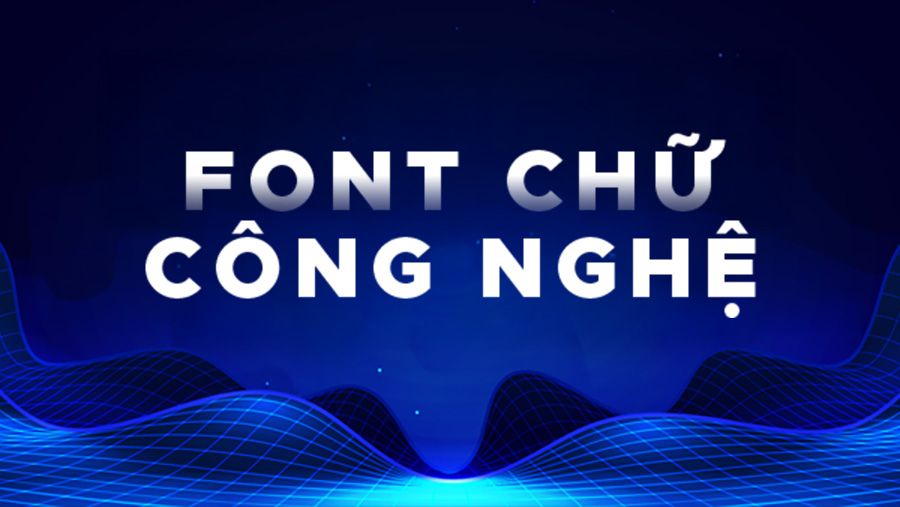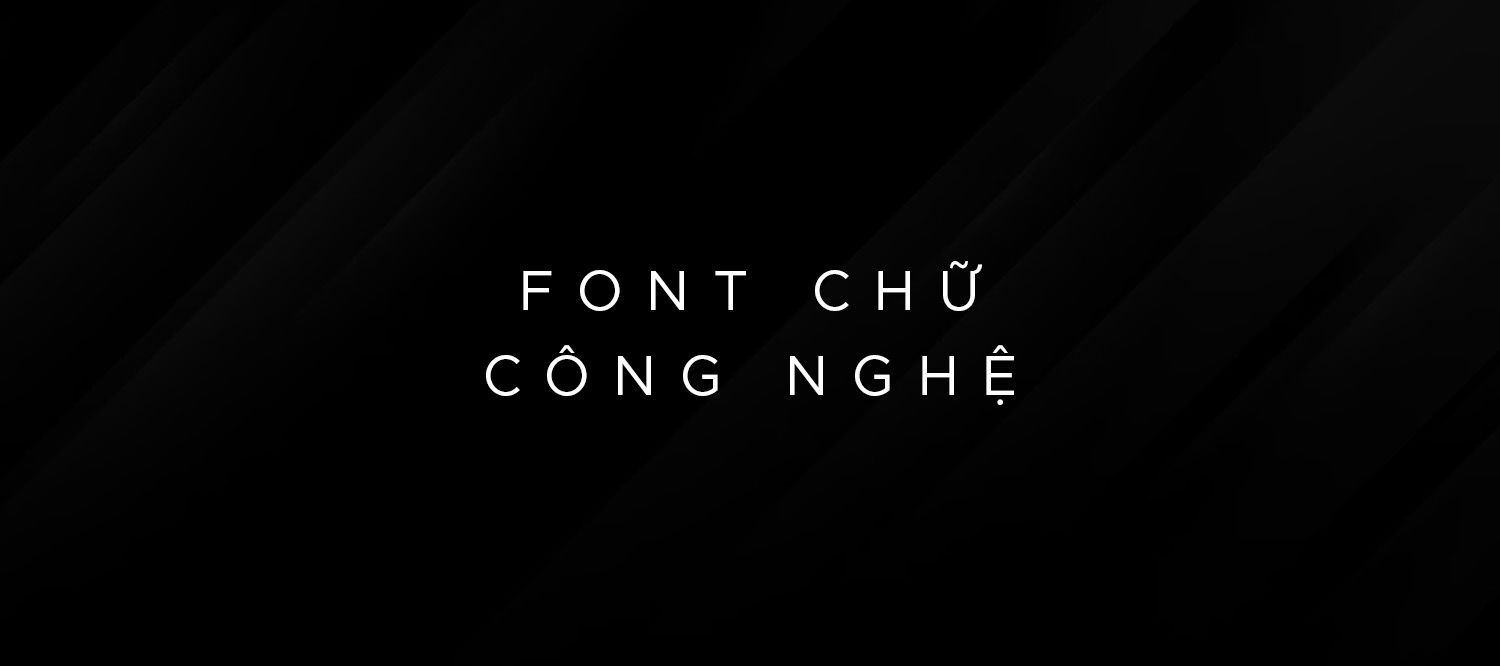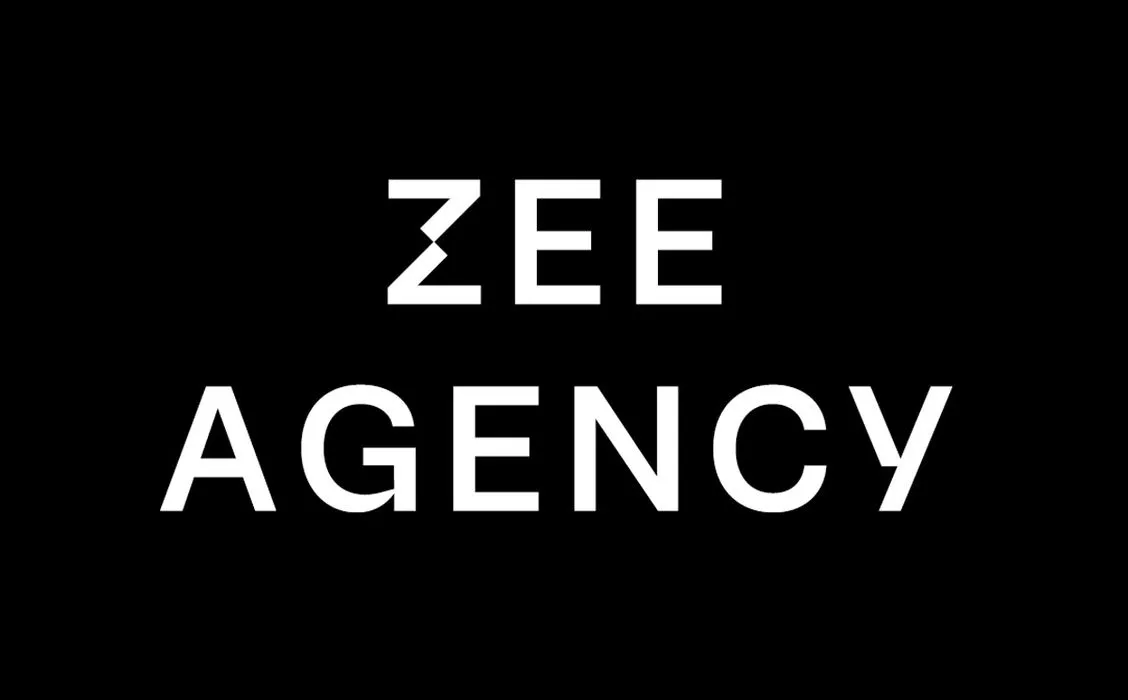
[Tải Xuống] 15+ Font Chữ Công Nghệ Việt Hóa Miễn Phí & Có Phí Mới Nhất 2025
Giới thiệu chung
Năm 2025, font chữ công nghệ nổi lên như một xu hướng quan trọng trong ngành thiết kế đồ họa. Không chỉ mang đến sự hiện đại, mạnh mẽ và đầy tính tương lai, những font này còn giúp designer truyền tải thông điệp sáng tạo trong nhiều lĩnh vực: từ UI/UX, branding, esports cho đến poster sự kiện công nghệ.
Điểm đặc biệt, nhiều bộ font đã được Việt hóa đầy đủ dấu tiếng Việt, nhờ đó trở nên thân thiện và dễ ứng dụng hơn cho cộng đồng thiết kế trong nước. Trong bài viết này, chúng ta sẽ cùng khám phá 15+ font chữ công nghệ miễn phí & có phí mới nhất 2025, kèm link tải trực tiếp từ S99.vn.
Font chữ công nghệ là gì?
Font chữ công nghệ (Technology Fonts) là khái niệm chỉ những kiểu chữ được thiết kế với đường nét góc cạnh, dứt khoát, mang hơi thở hiện đại và tương lai. Đặc trưng của chúng là tạo cảm giác mạnh mẽ, tinh gọn và giàu tính ứng dụng trong các sản phẩm số.
Các font này thường có cấu trúc chữ vuông vức, chắc chắn và đôi khi kết hợp hiệu ứng sáng, cắt chéo hoặc phong cách sans-serif tối giản. Nhờ sự đa dạng này, font chữ công nghệ trở thành lựa chọn hoàn hảo cho logo công nghệ, thương hiệu hiện đại, thiết kế UI/UX và poster mang hơi hướng sci-fi, futuristic.
Danh sách 15 font chữ công nghệ Việt hóa
1. Font chữ DFVN Pexel Grotesk Việt hóa – Hiện đại, tối giản và miễn phí
DFVN Pexel Grotesk đưa người xem quay lại nét đẹp của máy đánh chữ cổ điển nhưng đã được thổi vào hơi thở mới. Những đường chữ vuông vắn, gọn gàng tạo sự chắc chắn và tinh tế, vừa đủ để làm tiêu đề nổi bật nhưng cũng không kém phần thanh thoát cho UI hiện đại.
2. Font chữ VL Monologue Việt hóa – Cứng cáp, hiện đại cho thiết kế công nghệ
Điểm mạnh của SVN Cintra nằm ở sự đa năng. Với chữ dày, rõ nét, font này được ưa chuộng trong esports, game, xây dựng và cả cơ khí. Tính ứng dụng rộng cùng cảm giác hiện đại giúp nó luôn nằm trong top lựa chọn cho các dự án thiết kế chuyên nghiệp.
3. Font chữ công nghệ SVN Cintra Việt hóa – Mạnh mẽ và đa năng trong ứng dụng
Điểm mạnh của SVN Cintra nằm ở sự đa năng. Với chữ dày, rõ nét, font này được ưa chuộng trong esports, game, xây dựng và cả cơ khí. Tính ứng dụng rộng cùng cảm giác hiện đại giúp nó luôn nằm trong top lựa chọn cho các dự án thiết kế chuyên nghiệp.
4. Font chữ UTM Neutra Việt hóa miễn phí – Tối giản nhưng cực kỳ mạnh mẽ
UTM Neutra toát lên sự cân bằng giữa tối giản và sức mạnh. Những nét chữ vuông vức, sắc sảo tạo cảm giác vững chắc, rất hợp với thiết kế kiến trúc, branding công nghệ và poster quảng cáo cần sự sang trọng, hiện đại.
5. Font chữ SVN Kelso Việt hóa – Neon độc đáo, hiện đại và ấn tượng
SVN Kelso làm người ta liên tưởng đến những bảng đèn neon rực rỡ nơi phố thị về đêm. Hiệu ứng phát sáng độc đáo của font này cực kỳ phù hợp với game, nhạc hội hay những poster cần sự bắt mắt, sôi động.
6. Font chữ công nghệ SVN Mission X Việt hóa – Mạnh mẽ, đậm chất gaming
SVN Mission X mang đậm hơi thở của thế giới game và esports. Những đường chữ góc cạnh, dứt khoát truyền tải sức mạnh và tốc độ, khiến nó trở thành lựa chọn lý tưởng cho banner giải đấu, logo gaming hoặc thương hiệu công nghệ.
Việt hóa: SVN Team
7. Font chữ Zee Display Việt hóa – Không chân, tối giản và hiện đại
Zee Display mang đến sự rõ ràng và trực quan. Các đường chữ không chân dày, chắc giúp font giữ vững khả năng hiển thị sắc nét trên mọi thiết bị, từ giao diện ứng dụng đến poster quảng cáo công nghệ.
Tác giả gốc: Nach Oh!
Việt hóa: Team Zee
8. Font chữ TH Radley Sans Việt hóa – Thể thao khỏe khoắn và mạnh mẽ
TH Radley Sans toát lên tinh thần thể thao với từng đường chữ khỏe khoắn. Sự mạnh mẽ trong thiết kế khiến font trở thành công cụ đắc lực cho banner esports, logo phòng gym hay các dự án branding năng động.
Tác giả gốc: Mukhlis Muhammad
Việt hóa: TH Team
9. Font chữ TH Bernat Việt hóa – Serif thanh lịch kết hợp hiện đại
TH Bernat là sự hòa quyện giữa cổ điển và hiện đại. Với đặc trưng serif tinh tế, font này phù hợp cho các thương hiệu công nghệ cao cấp, tạp chí chuyên ngành và những thiết kế cần sự sang trọng, trang nhã.
10. Font chữ slab serif TH Blayzer Việt hóa – Cứng cáp, công nghiệp và nổi bật
Kết luận
Trên đây là danh sách 15+ font chữ công nghệ miễn phí & có phí mới nhất 2025 đã được Việt hóa, sẵn sàng cho các dự án sáng tạo. Từ phong cách tối giản, khỏe khoắn cho đến neon rực rỡ hay sci-fi futuristic, mỗi font đều mang một cá tính riêng.